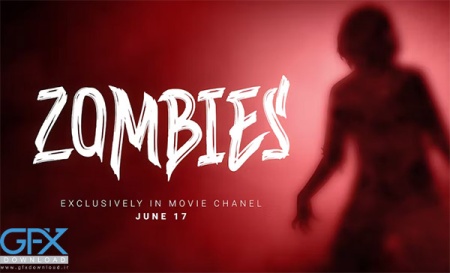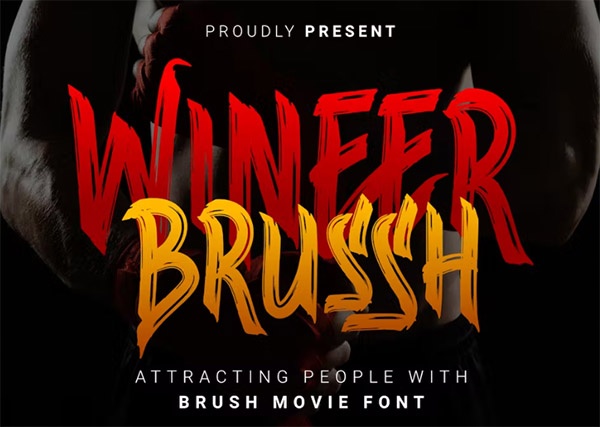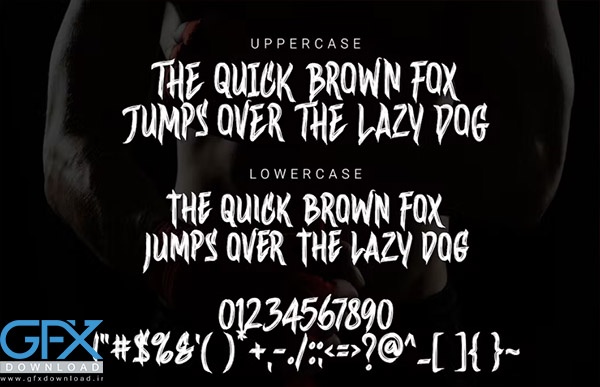
فونت انگلیسی رایگان با طراحی براش Wineer Brush
فونت رایگان با طراحی براش Wineer Brush
دانلود رایگان فونت انگلیسی ترسناک با طراحی براش Wineer Brush
Wineer Brush یک فونت انگلیسی با طراحی براش است که به طور منحصر به فرد ساخته شده است و دارای ویژگی بافت شگفت انگیزی است که آن را برای همکاری با پروژه های شما عالی می کند. یک فونت نمایش زیبا و پررنگ. فونت انگلیسی رایگان با طراحی براش Wineer Brush با طراحی منحصر به فرد خود امکان استفاده از ان در تمامی طرح های گرافیکی به خصوص پوستر ها،جلد ها و تایپوگرافی ها می باشد.
فونت رایگان انگلیسی با طراحی براش Wineer Brush
دانلود فونت ترسناک Wineer Brush
Wineer Brussh فونتی ترسناک است که به حروف بزرگ، کوچک، لیگاتور و چند زبانه مجهز شده است که برای عناوین فیلم، فیلم، عناوین ترسناک، اکشن، فانتزی و هیجانی مانند مثال در تصویر پیش نمایش بالا مناسب است.
• نام فونت: Wineer Brussh
• گلیف های استاندارد
• متناوب
• لیگاتور
• لهجه چند زبانه